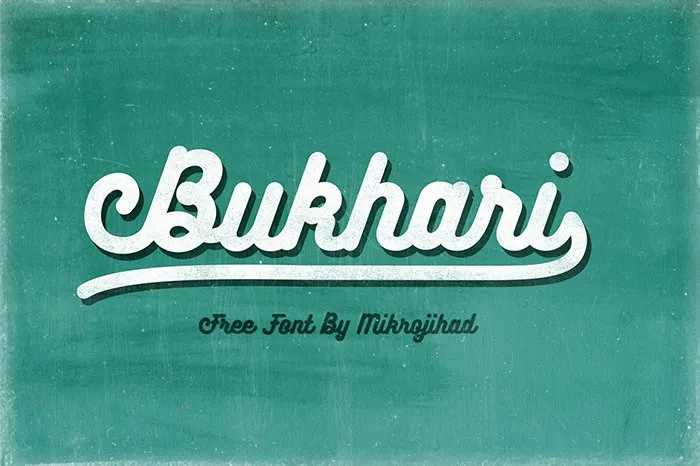
Bukhari font – Fonte Grátis
Bukhari font
A Bukhari Script é uma elegante fonte cíliada monoline que traz um toque moderno às suas criações digitais. É tão poderosa quanto ela é leve, combinando um forte contraste com linhas sólidas e um traço fluido em movimento. Essa fonte vem da inspiração de uma linha bold criada a partir de um simples clic do mouse na tela, dando origem a um estilo que se assemelha ao desenho feito por uma letra tipográfica de rato. Hamilton é o designer por trás dessa maravilhosa criação, e ele chama essa fonte de “Mouse Lettering Typeface” – um nome que resume perfeitamente seu processo criativo. Esta fonte não apenas adiciona profundidade a qualquer projeto, mas também dá vida aos textos digitais através da arte do desenho. Seja para o layout de uma página ou o design de um produto digital, Bukhari Script oferece um gás único que torna as suas criações imensuravelmente interessantes e vivas.